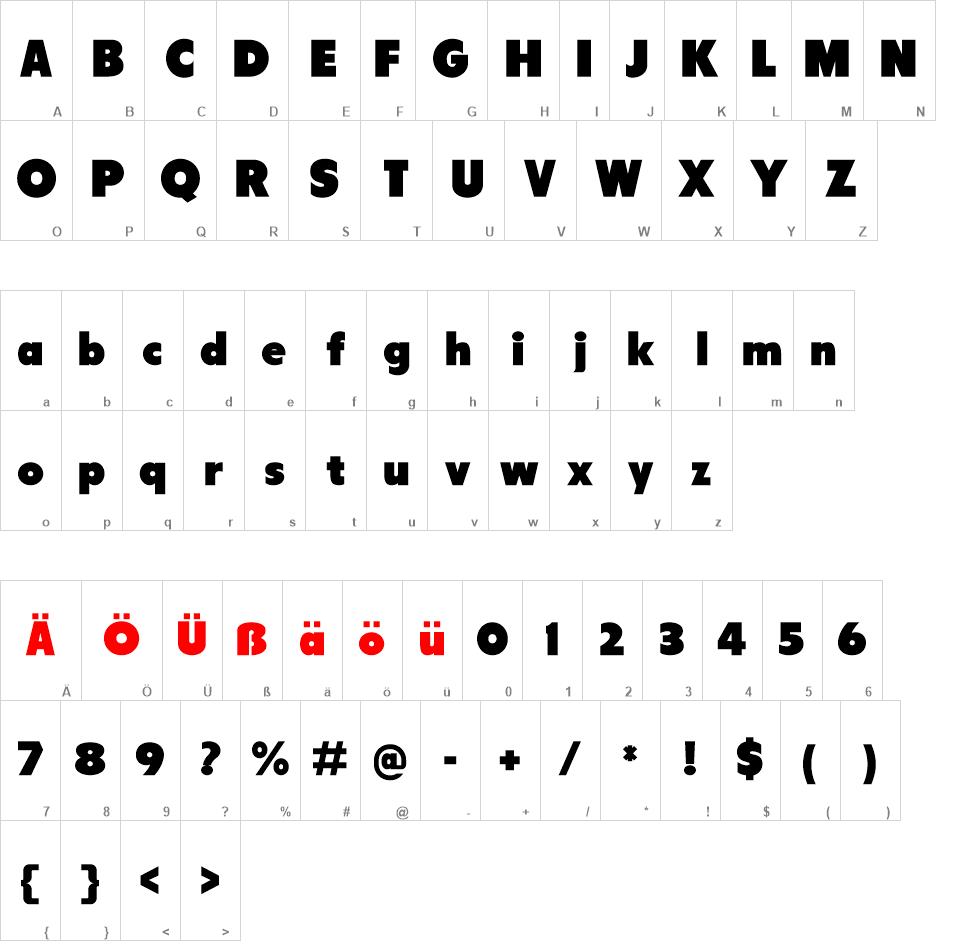
Tondu
Eine vielseitige Displayschrift, die klassische Proportionen mit modernem Styling verbindet. Durch den präzisen Letter Fit ist es perfekt für den Einsatz auf Schildern, Buchumschlägen, Verpackungen, Plakaten und T-Shirts geeignet. Zu den Details gehören ein vollständiger Zeichensatz, ein manuell bearbeitetes Kerning und ein Euro-Symbol.